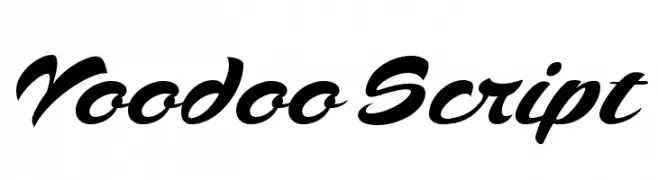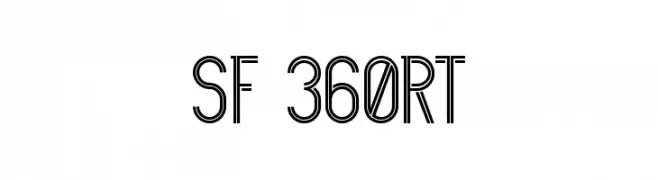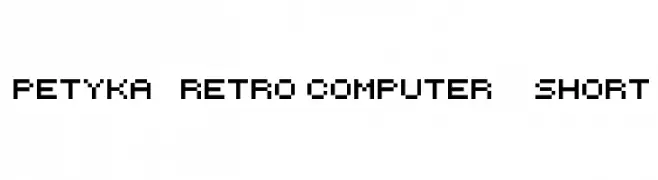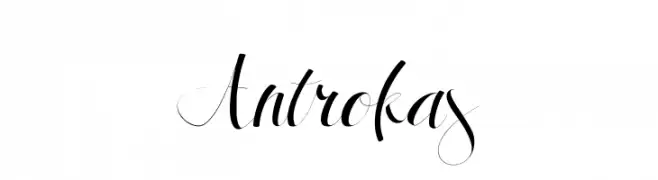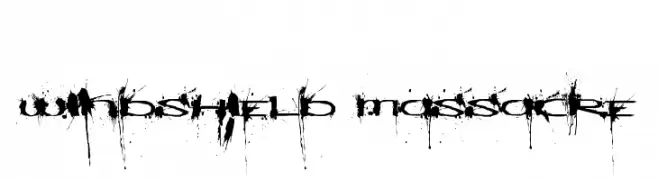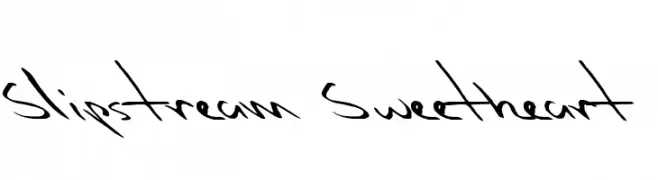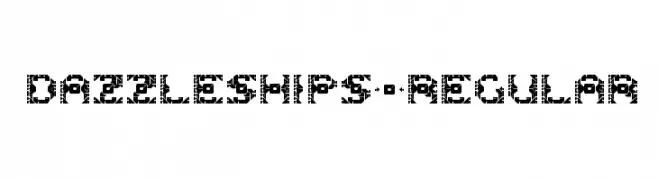
A bold, grungy font with splattered, chaotic elements for an edgy look.
A dynamic, handwritten font with expressive, fluid strokes.
A bold, cursive script font with elegant, flowing strokes and ornate details.
A bold, geometric font with intricate dazzle patterns in each character.
近期热门包括 Voodoo Script, SF 360RT, lalo, Petyka - Retro Computer___SHORT and Antrokas 它们在清晰度与个性之间取得平衡,适用于科技品牌、编辑排版与社媒视觉。